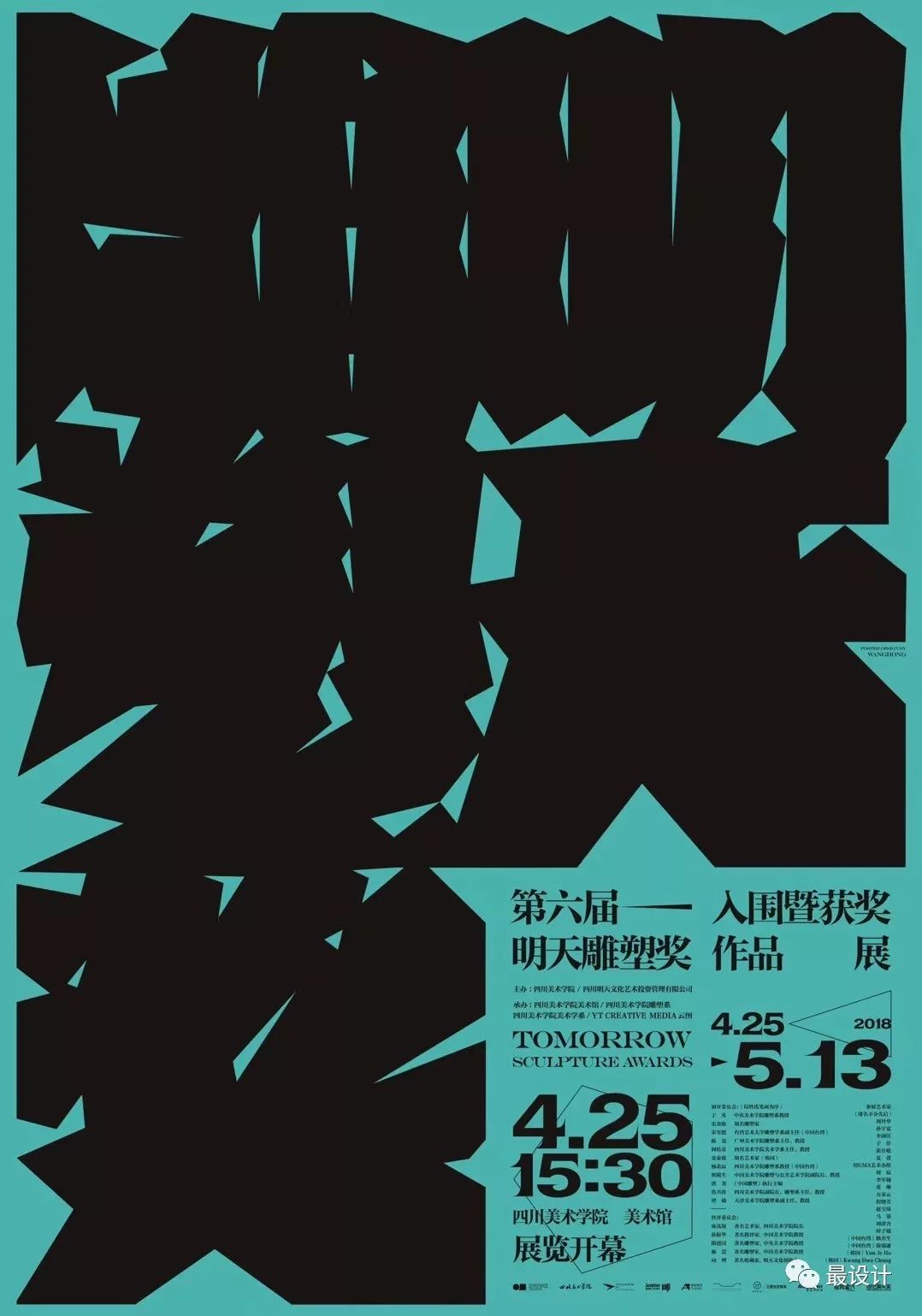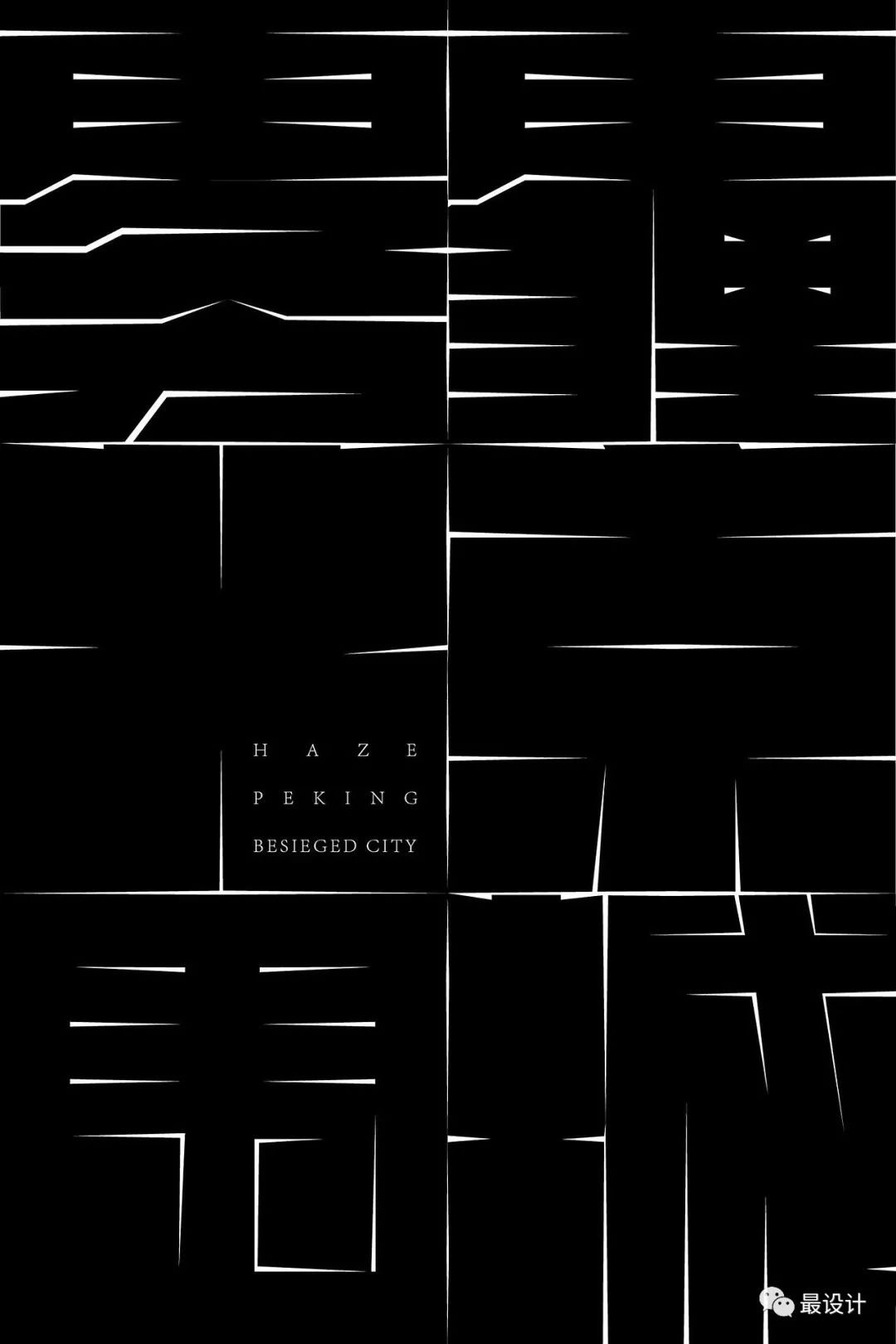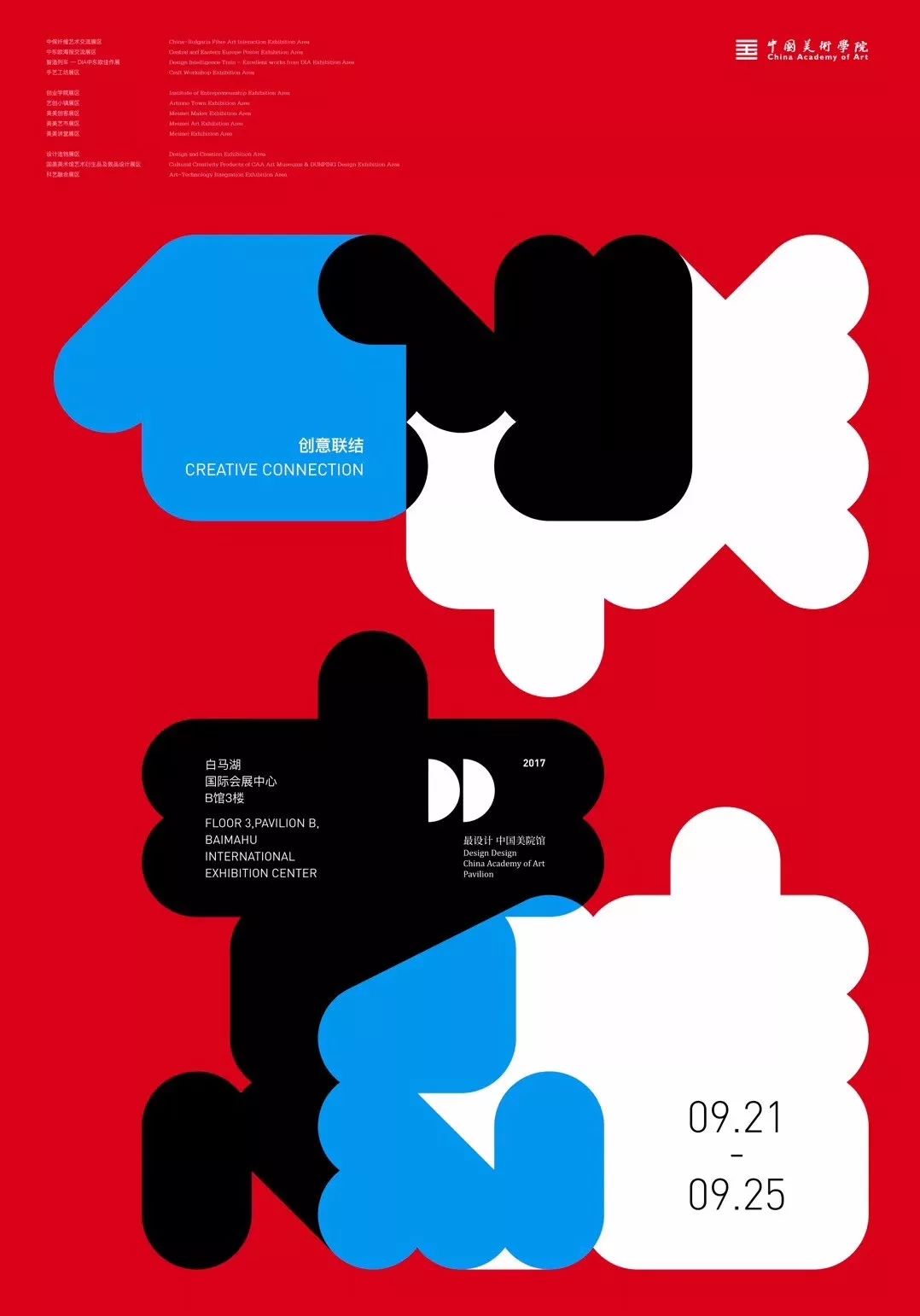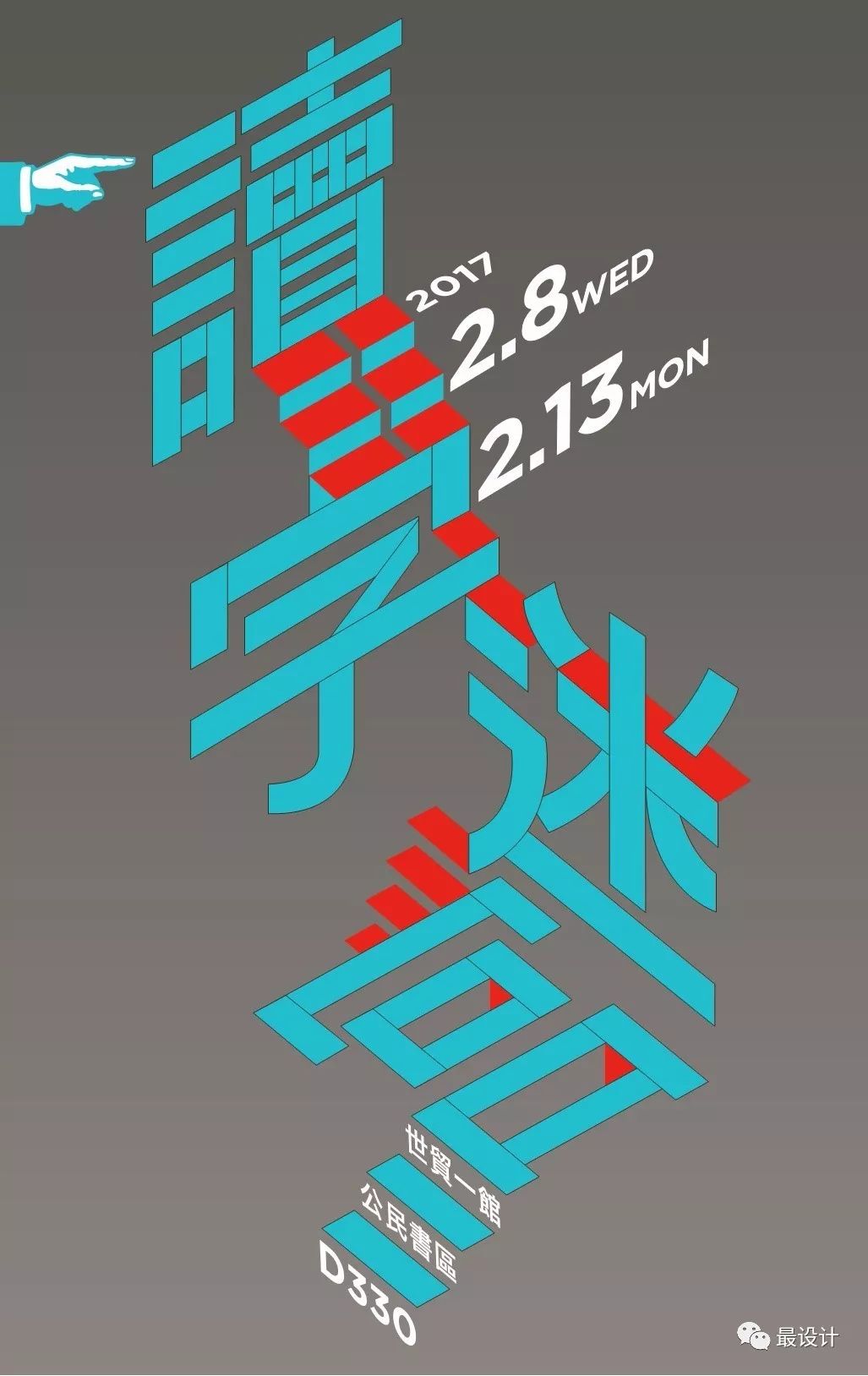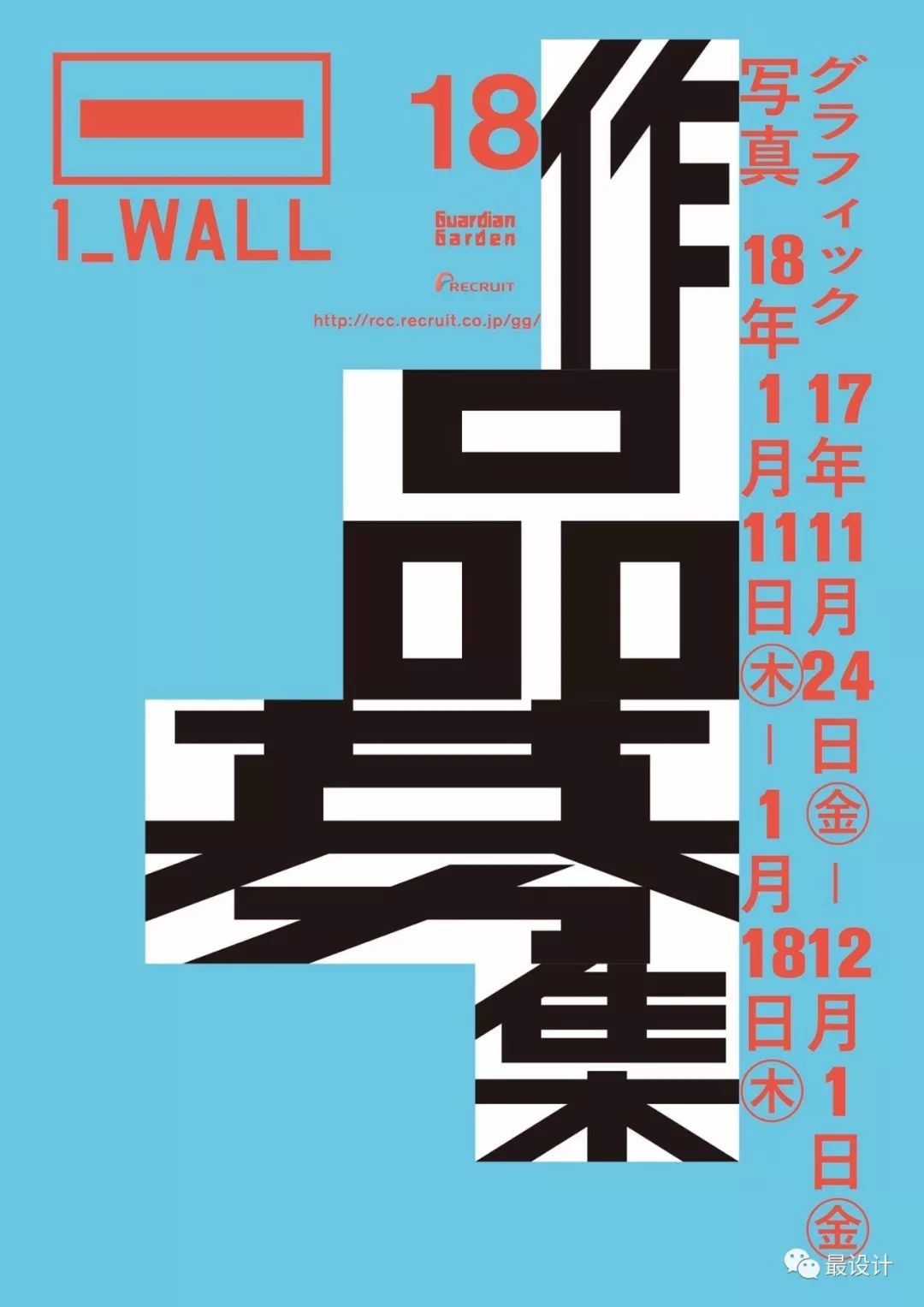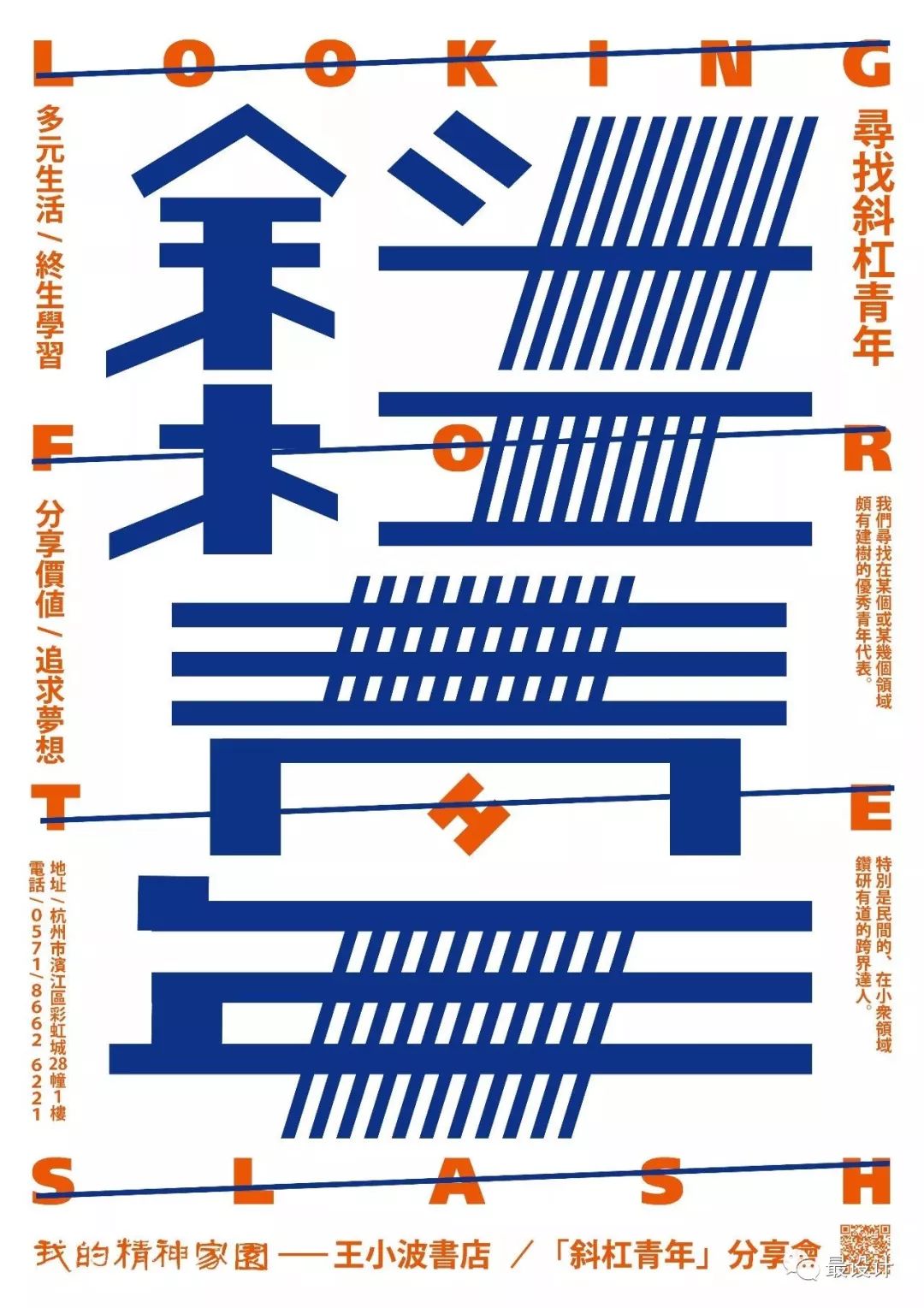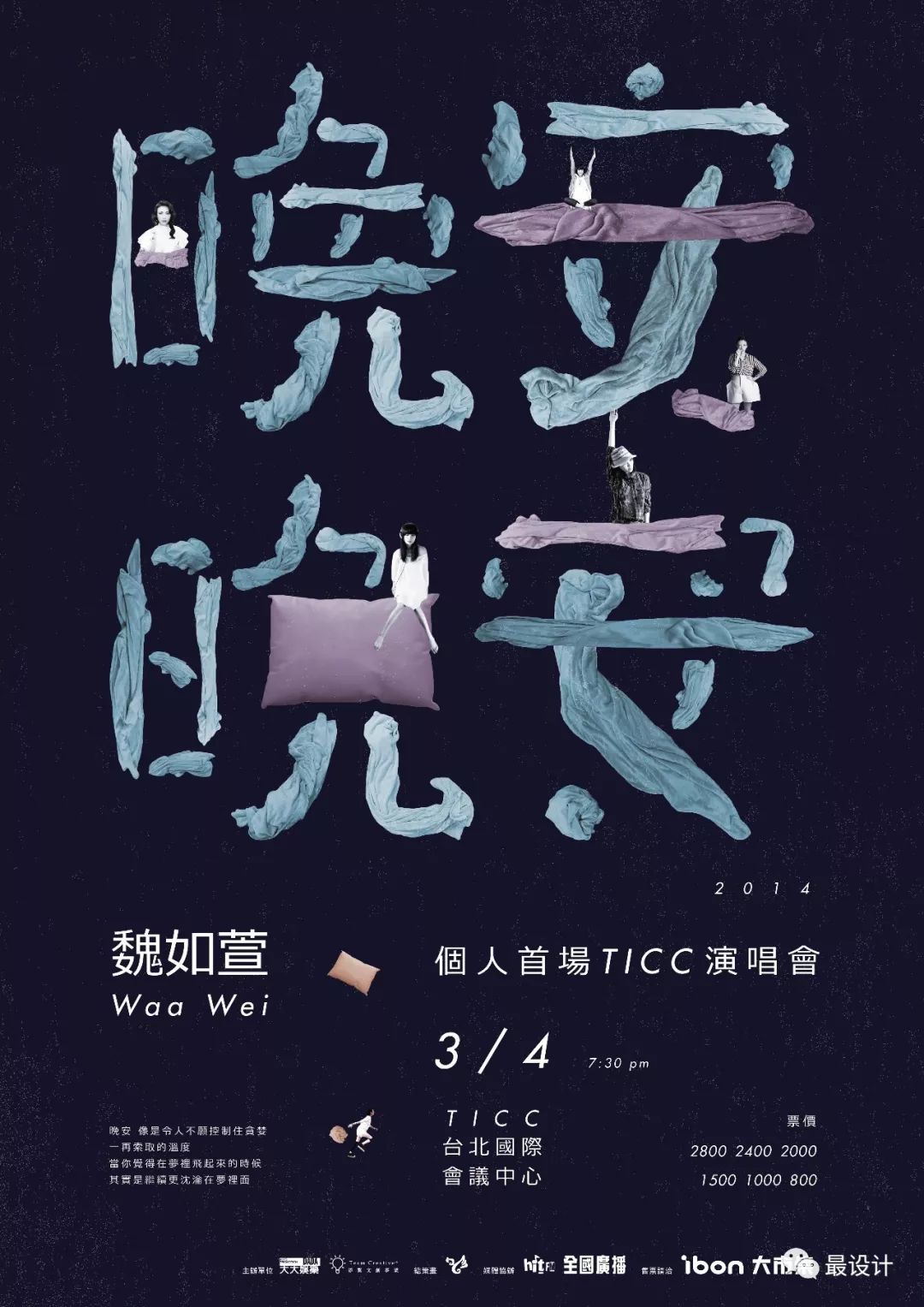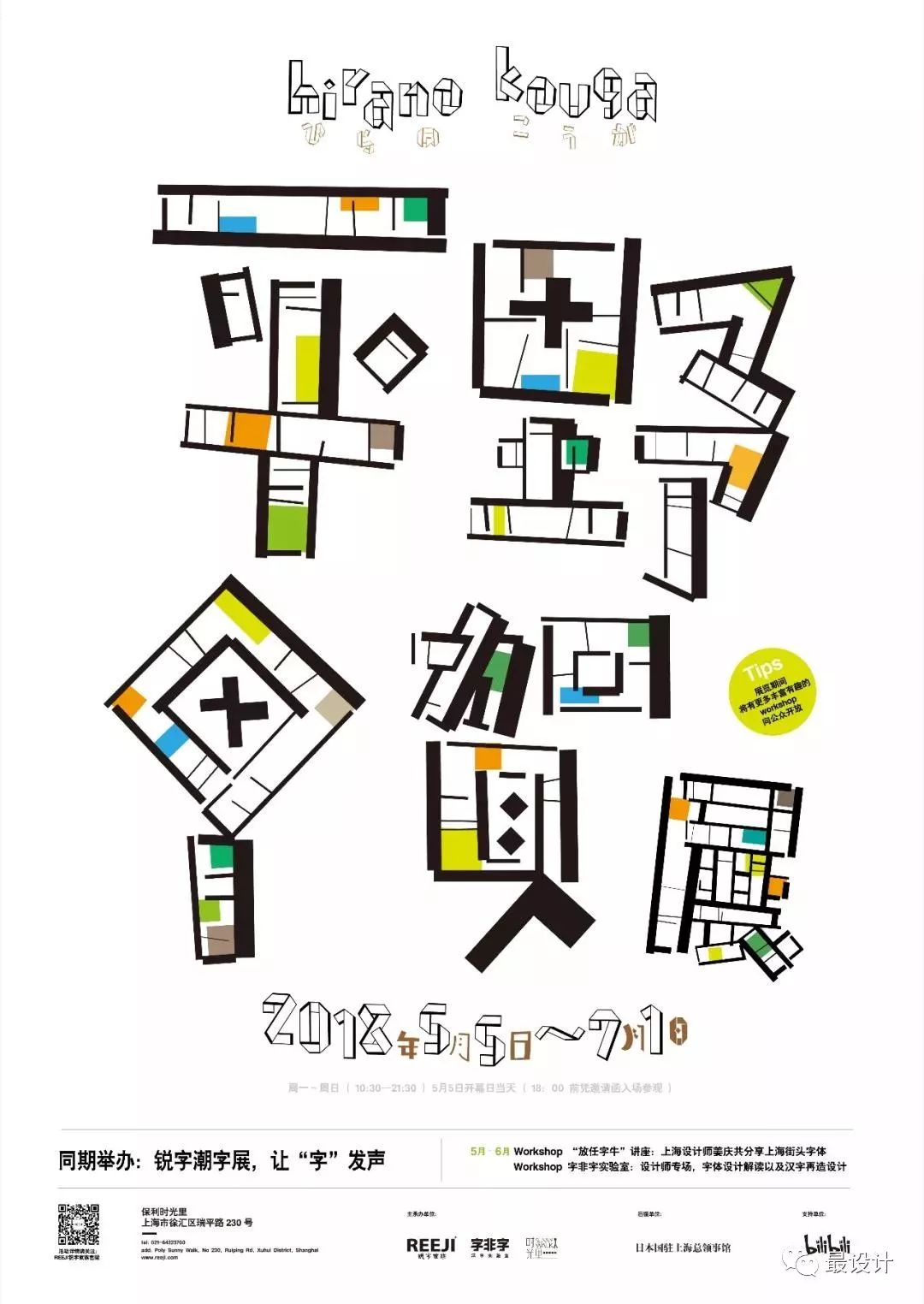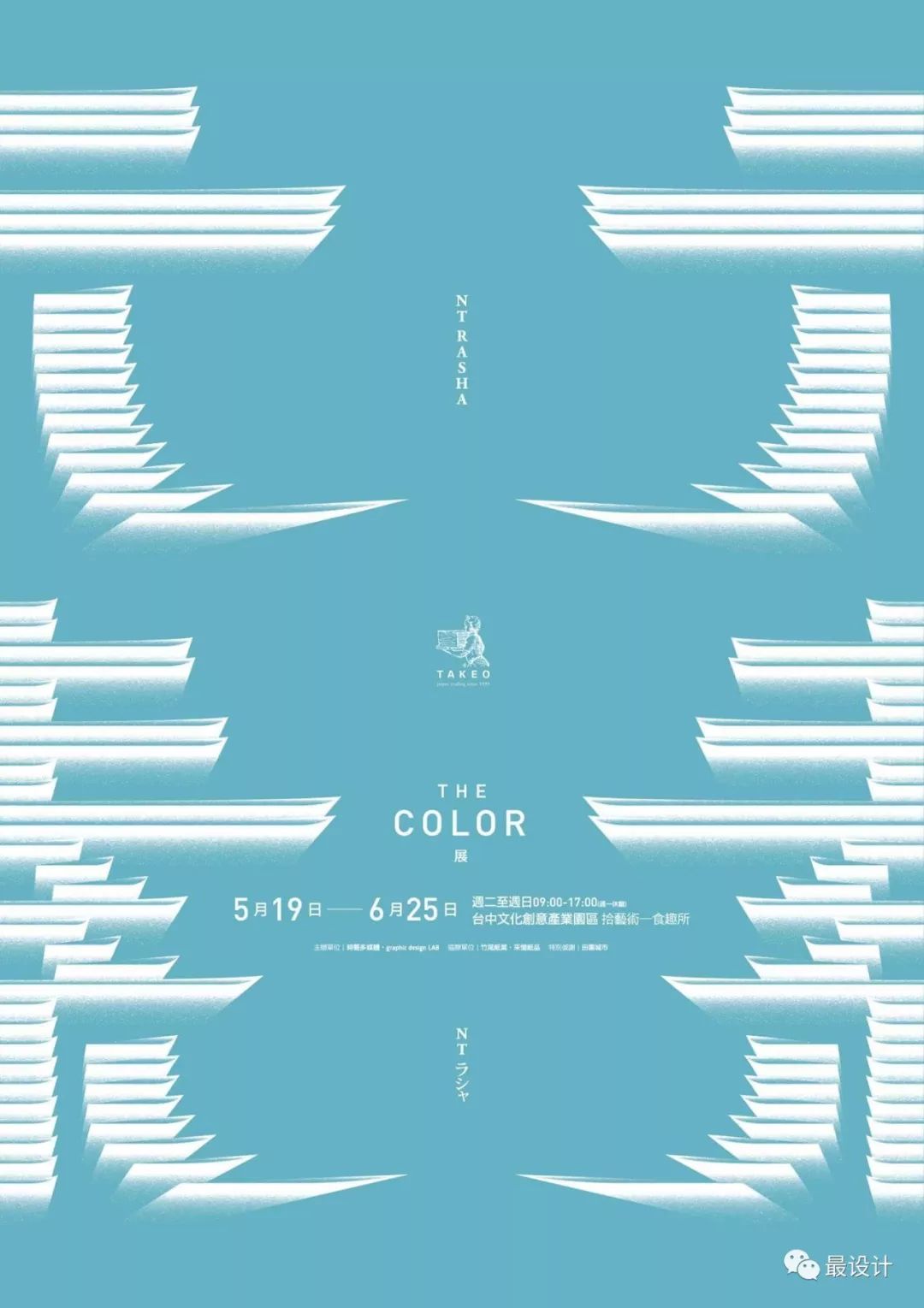
这些海报只用了一种元素——字体
设计时没有图片怎么办?
字体经过设计精心之后
它就成了版面的主图形
我们来看设计们的鬼斧神工
雾霾围城
第六届明天雕塑奖入围作品暨获奖作品展
记叙黑桥
快速东京
共命鳥清河、迦陵頻伽平井
设计:羽田纯
创意联结
设计:吴炜晨
传统的激进——现代中国文字设计的诞生
CO1設計2018展
读字迷宮
吉原治良赏
设计:杉崎真之助
现代版画展
设计:杉崎真之助
灰階城市 Grayscale City
意行2018,气韵东方中韩设计大展
中国艺术海外传播中的策展
设计:曹馨予
岡山芸術回廊
跨樂教室
镜像
说技
晚安晚安
新居浜活性化计画
1_WALL 作品征集
一期一会
岡本太郎
斜杠青年
设计:张弥迪
上海视觉艺术学院讲座
设计:张弥迪
不料
解明空気正体
音乐
元素The Color展
秋冬春夏
设计:fnt工作室
城塞
海鰻荘奇談 香山滋傑作選
设计:水户部功
中日韩水墨元素作品大展
长江艺术与设计学院优秀研究生作品展
猿——恭贺新年
第一届橼椛文艺营
平野甲贺上海展
中国美术学院90年校庆
温故非遗手工艺展第六回
设计:形而上